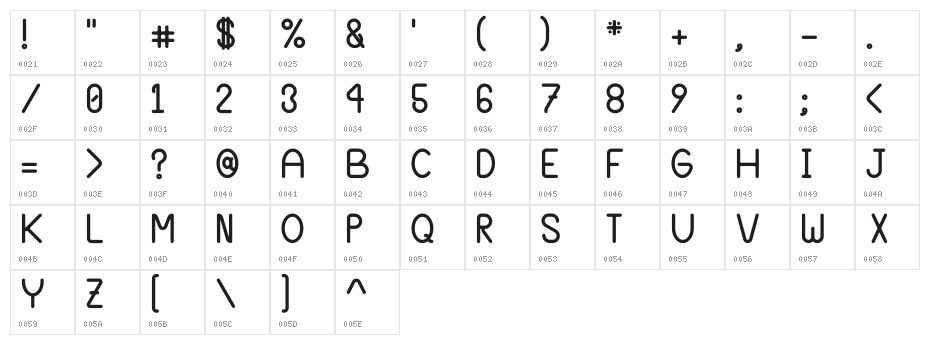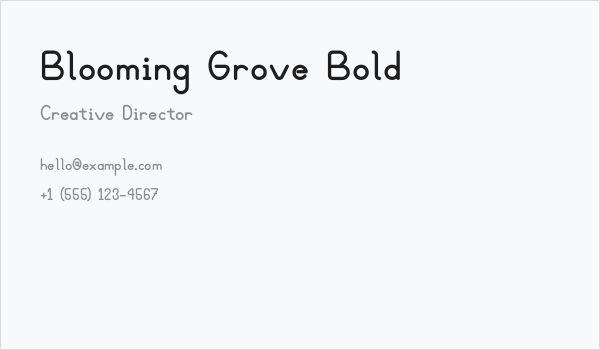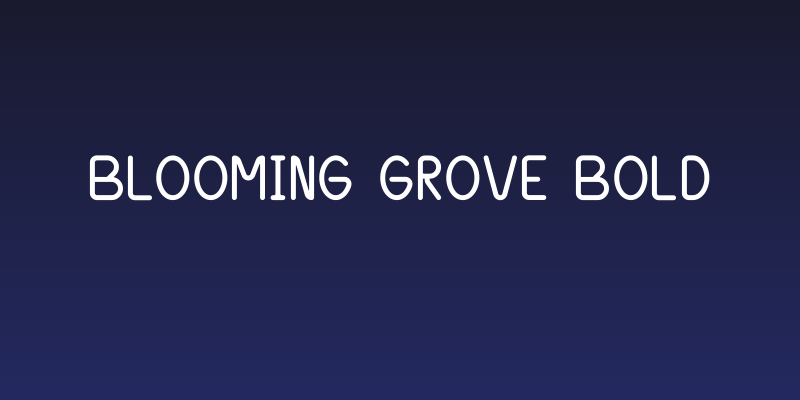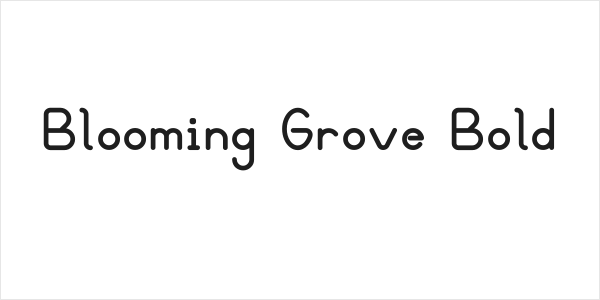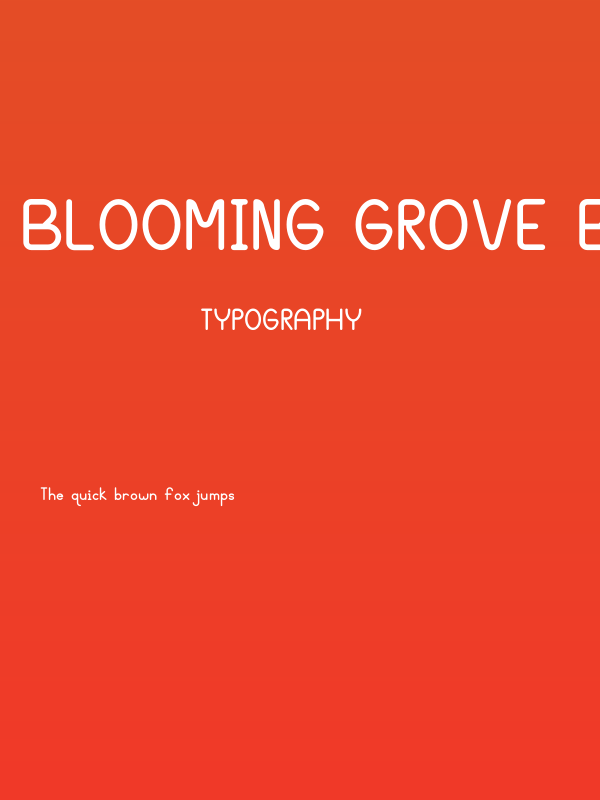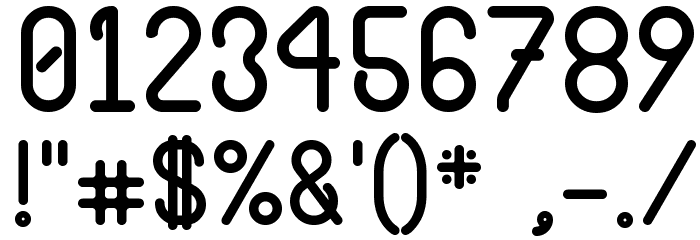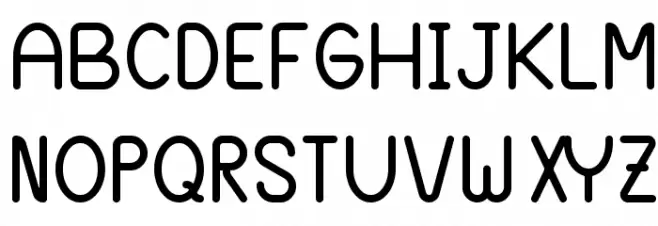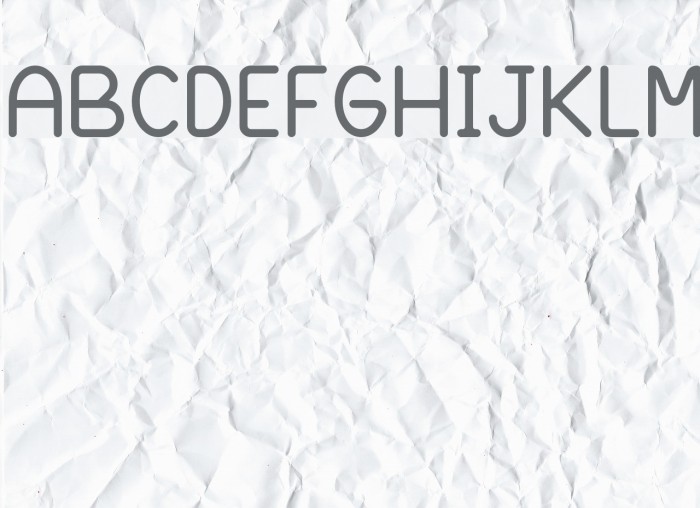
Blooming Grove Bold Font
| Stile generale | Modern, Playful |
| Progetti proposti | Ideal for children's books, playful branding, casual invitations, and creative posters. |